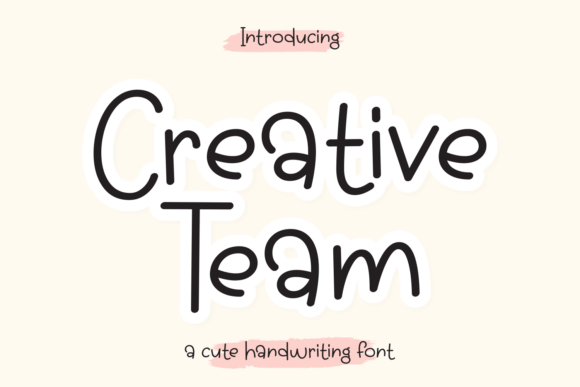
Creative Team
การค้นหาองค์ประกอบการออกแบบที่เหมาะสมอาจเป็นเรื่องท้าทาย แต่ Creative Team นำเสนอคอลเลกชันที่โดดเด่นซึ่งช่วยยกระดับงานของคุณได้ทันที
ไม่ว่าคุณจะสร้างผลิตภัณฑ์ POD (Print on Demand) คำเชิญงานแต่งงาน หรือกราฟิกโซเชียลมีเดีย Creative Team ก็เหมาะสมอย่างยิ่ง